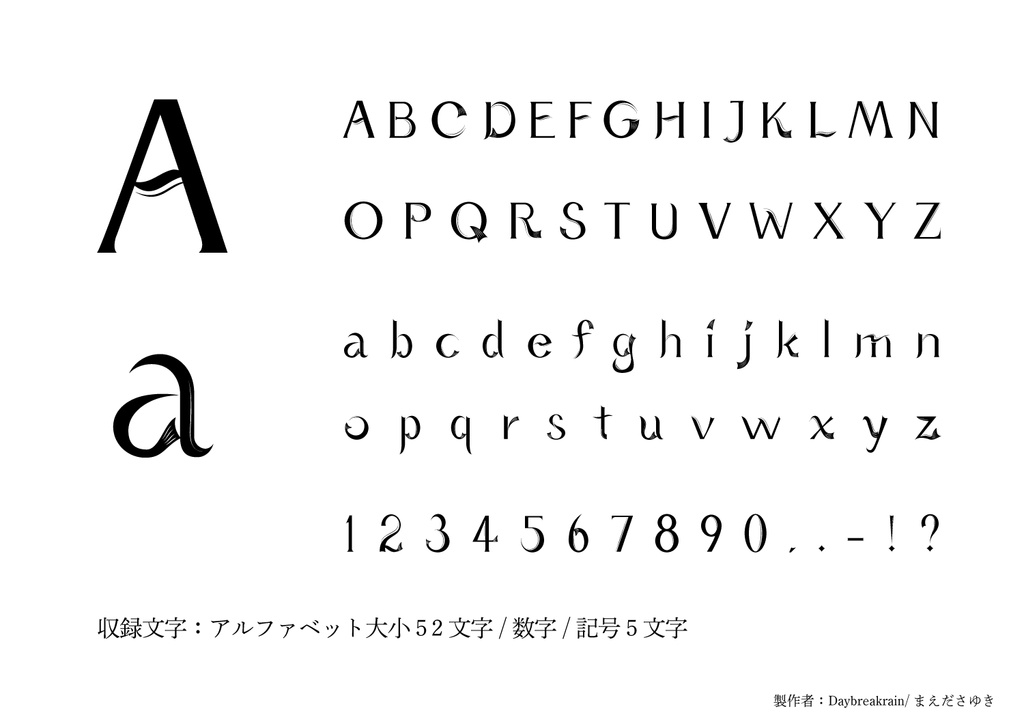
おさかなフォント
おさかなフォント 『魚の尾ひれと波』をモチーフに制作した書体です。 題字やロゴなどに使用すると映えます。 可読性は低いデザイン書体になりますので長文には向きません。 必ずreadmeと書かれたテキストファイルをお読みになってからご利用ください。 【収録文字】 ・アルファベット大小52文字 ・数字 ・記号少量 ファイル名は「Fish_Font」となっています。 データはOTFデータです。 【免責事項】 ・商業、個人問わずご利用できます。 ・再配布、商標登録、複製、改変不可 ・利用の際の報告は任意です 。 おさかなフォントの著作権は全てdaybreakrain/まえださゆきに帰属します。 自作発言等はお控え下さい。 また、利用者様が当フォントを利用した際に負った問題、損害について作者は一切の責任を負いません。 フォントをダウンロードした時点で利用規約に同意したものと見なします。 ご利用は自己責任でお願い致します。 通常版と投げ銭版のデータは同じものです。 フリーフォントとして配布しますが、もしよろしければ投げ銭版からお好みでBoostしてご支援いただけますと嬉しいです。 励みにさせていただきます。 更新履歴 2020.8.21 おさかなフォントVer.1.00配布